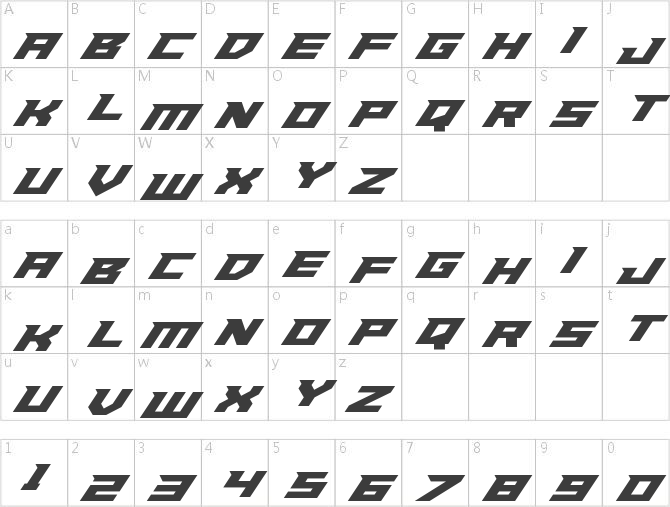
字体名称: Paladin
Paladins Super-Italic
Paladins Super-Italic介绍
Paladins Super-Italic字体字库是一款让人赏心悦目、百看不厌的英文字体,适合各类广告和产品包装设计应用,字体大小0.02MB,格式为ttf字体,上传用户是哼哼哈兮,作者/版权方为未知
Paladins Super-Italic效果图